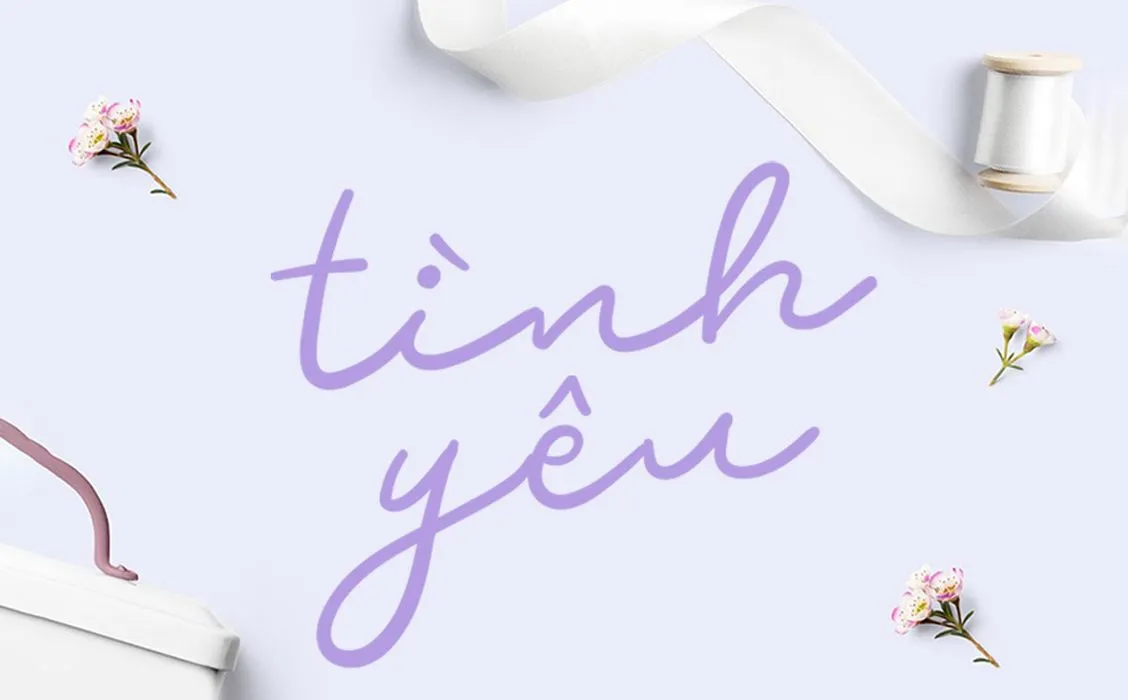
SVN Dear Jane là font chữ viết tay mềm mại mang vẻ đẹp tự nhiên, thanh lịch và giàu cảm xúc, phù hợp với nhiều dự án thiết kế sáng tạo. Những đường nét uyển chuyển, phóng khoáng của font giúp nội dung trở nên gần gũi như được viết bằng tay, đồng thời vẫn giữ được sự tinh tế cần thiết cho các ấn phẩm chuyên nghiệp.
Nếu bạn đang tìm kiếm một kiểu chữ có thể truyền tải cảm giác lãng mạn, nhẹ nhàng và mang dấu ấn cá nhân, SVN Dear Jane là lựa chọn đáng cân nhắc. Font đặc biệt phù hợp với thiệp cưới, logo, bao bì, nội dung mạng xã hội, poster, tiêu đề và nhiều sản phẩm thiết kế hướng đến vẻ đẹp thủ công.
Font chữ viết tay mềm mại SVN Dear Jane dành cho thiết kế thanh lịch và giàu cảm xúc
Font chữ viết tay mềm mại SVN Dear Jane gây ấn tượng nhờ phong cách tự nhiên, giống những nét bút được tạo ra một cách ngẫu hứng trên giấy. Thay vì sử dụng cấu trúc cứng nhắc, font tập trung vào sự chuyển động linh hoạt giữa các ký tự, qua đó tạo nên cảm giác thân thiện, chân thành và có chiều sâu cảm xúc.
SVN Dear Jane có thể trở thành điểm nhấn trong những bố cục cần sự nữ tính, tinh tế hoặc lãng mạn. Khi được kết hợp với hình ảnh, màu sắc và khoảng trắng phù hợp, kiểu chữ này giúp thiết kế trở nên mềm mại hơn mà không làm mất đi tính rõ ràng của thông điệp. Đây cũng là một lựa chọn hữu ích cho nhà thiết kế, người sáng tạo nội dung, chủ cửa hàng và thương hiệu muốn xây dựng hình ảnh gần gũi với khách hàng.
Phong cách chữ viết tay tự nhiên và mềm mại
Điểm nổi bật nhất của SVN Dear Jane nằm ở những đường nét viết tay thanh thoát, có độ nghiêng và nhịp điệu tự nhiên. Hình dáng ký tự không quá khuôn mẫu, tạo cảm giác như mỗi từ đều được viết bằng bút thay vì hình thành từ một bộ chữ kỹ thuật số. Nhờ đặc điểm này, nội dung sử dụng SVN Dear Jane dễ tạo thiện cảm và mang dấu ấn cá nhân rõ rệt.
Vẻ mềm mại của font rất phù hợp với các chủ đề liên quan đến tình yêu, thời trang, làm đẹp, phong cách sống, hoa lá, quà tặng và sản phẩm thủ công. Trong những thiết kế cần truyền tải câu chuyện hoặc cảm xúc, font có thể giúp thông điệp trở nên chân thành hơn. Người dùng có thể lựa chọn SVN Dear Jane cho một câu trích dẫn, lời chúc, tên thương hiệu hoặc tiêu đề ngắn để làm nổi bật nét duyên dáng của bố cục.
Tạo điểm nhấn ấn tượng cho tiêu đề và thông điệp
SVN Dear Jane phát huy hiệu quả khi được dùng làm tiêu đề, câu nhấn mạnh hoặc nội dung có độ dài vừa phải. Những nét chữ uyển chuyển giúp thu hút ánh nhìn và tạo sự khác biệt so với các font sans serif hoặc serif thông thường. Trong cùng một thiết kế, bạn có thể sử dụng SVN Dear Jane cho phần tiêu đề, sau đó kết hợp với một kiểu chữ đơn giản hơn ở phần nội dung để duy trì khả năng đọc.
Một số vị trí ứng dụng phù hợp của font chữ viết tay SVN Dear Jane gồm:
- Tên thương hiệu, logo chữ và slogan ngắn.
- Tiêu đề poster, banner, tờ rơi hoặc bảng giới thiệu sản phẩm.
- Câu trích dẫn, lời chúc và nội dung tạo cảm hứng trên mạng xã hội.
- Tên cô dâu, chú rể hoặc thông điệp nổi bật trên thiệp cưới.
- Nhãn sản phẩm, bao bì, thẻ cảm ơn và ấn phẩm nhận diện thương hiệu.
Để kiểu chữ thể hiện tốt nhất, nhà thiết kế nên ưu tiên những câu ngắn, kích thước chữ đủ lớn và khoảng cách bố cục thông thoáng. Cách sử dụng này vừa làm nổi bật vẻ đẹp của từng nét chữ, vừa hạn chế cảm giác rối mắt khi thiết kế chứa nhiều thông tin.
Ứng dụng linh hoạt trong thiết kế in ấn và nội dung số
Font chữ viết tay mềm mại SVN Dear Jane có thể được khai thác trong nhiều dự án, từ sản phẩm in ấn truyền thống đến nội dung truyền thông trên nền tảng số. Với thiệp mời và thiệp cưới, font mang đến cảm giác trang trọng nhưng vẫn gần gũi. Trong thiết kế bao bì, kiểu chữ giúp sản phẩm tạo ấn tượng thủ công, tinh tế và có câu chuyện riêng.
Đối với nội dung kỹ thuật số, SVN Dear Jane phù hợp để thiết kế ảnh bài đăng Facebook, Instagram, Pinterest, video ngắn, ảnh bìa hoặc thumbnail. Font cũng có thể xuất hiện trong banner website, tiêu đề landing page hoặc hình ảnh quảng cáo, đặc biệt khi thương hiệu hướng đến nhóm khách hàng yêu thích phong cách nhẹ nhàng và giàu tính thẩm mỹ.
- Sử dụng làm tiêu đề chính để thu hút sự chú ý ngay từ cái nhìn đầu tiên.
- Kết hợp cùng bảng màu pastel, màu đất hoặc màu trung tính để tăng cảm giác thanh lịch.
- Phối với font chữ tối giản cho nội dung dài nhằm bảo đảm khả năng đọc.
- Duy trì khoảng trắng hợp lý để các nét viết tay có không gian thể hiện.
- Kiểm tra thiết kế ở cả kích thước in và màn hình trước khi xuất bản.
Tính linh hoạt này giúp SVN Dear Jane trở thành một tài nguyên hữu ích cho cả nhà thiết kế chuyên nghiệp lẫn người dùng không chuyên. Chỉ cần lựa chọn đúng kích thước, màu sắc và vị trí, bạn có thể tạo ra một sản phẩm trực quan có cá tính mà không cần bổ sung quá nhiều chi tiết trang trí.
Hỗ trợ xây dựng hình ảnh thương hiệu gần gũi
Typography đóng vai trò quan trọng trong việc định hình cảm nhận của khách hàng về thương hiệu. Một kiểu chữ viết tay như SVN Dear Jane có thể gợi lên sự tận tâm, thân thiện và cá nhân hóa. Đây là những giá trị phù hợp với thương hiệu thời trang, mỹ phẩm, studio cưới, tiệm bánh, cửa hàng hoa, sản phẩm handmade, quà tặng hoặc dịch vụ sáng tạo.